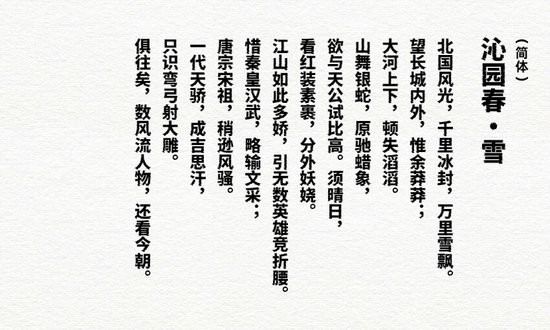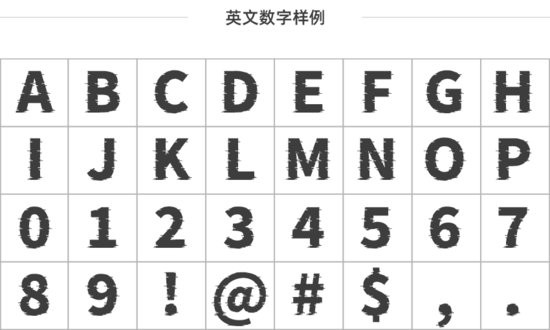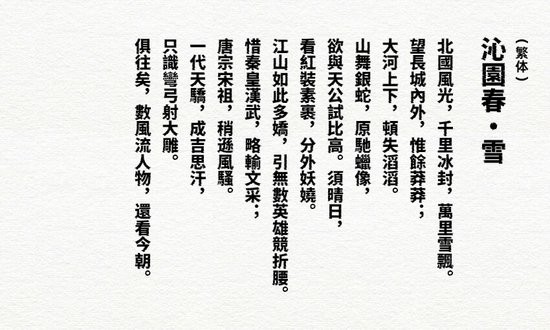
貓啃網(wǎng)故障黑字體是非常炫酷的故障風(fēng)的黑體字體,整個(gè)字體充滿了濃郁的賽博朋克的風(fēng)格,讓用戶可以在自己的設(shè)計(jì)之中融入濃濃的科幻風(fēng)格,軟件獲得許可免費(fèi)商用,用戶可以放心下載。
貓啃網(wǎng)故障黑基于思源黑體改造,采用SIL Open Font License 1.1授權(quán)發(fā)表。